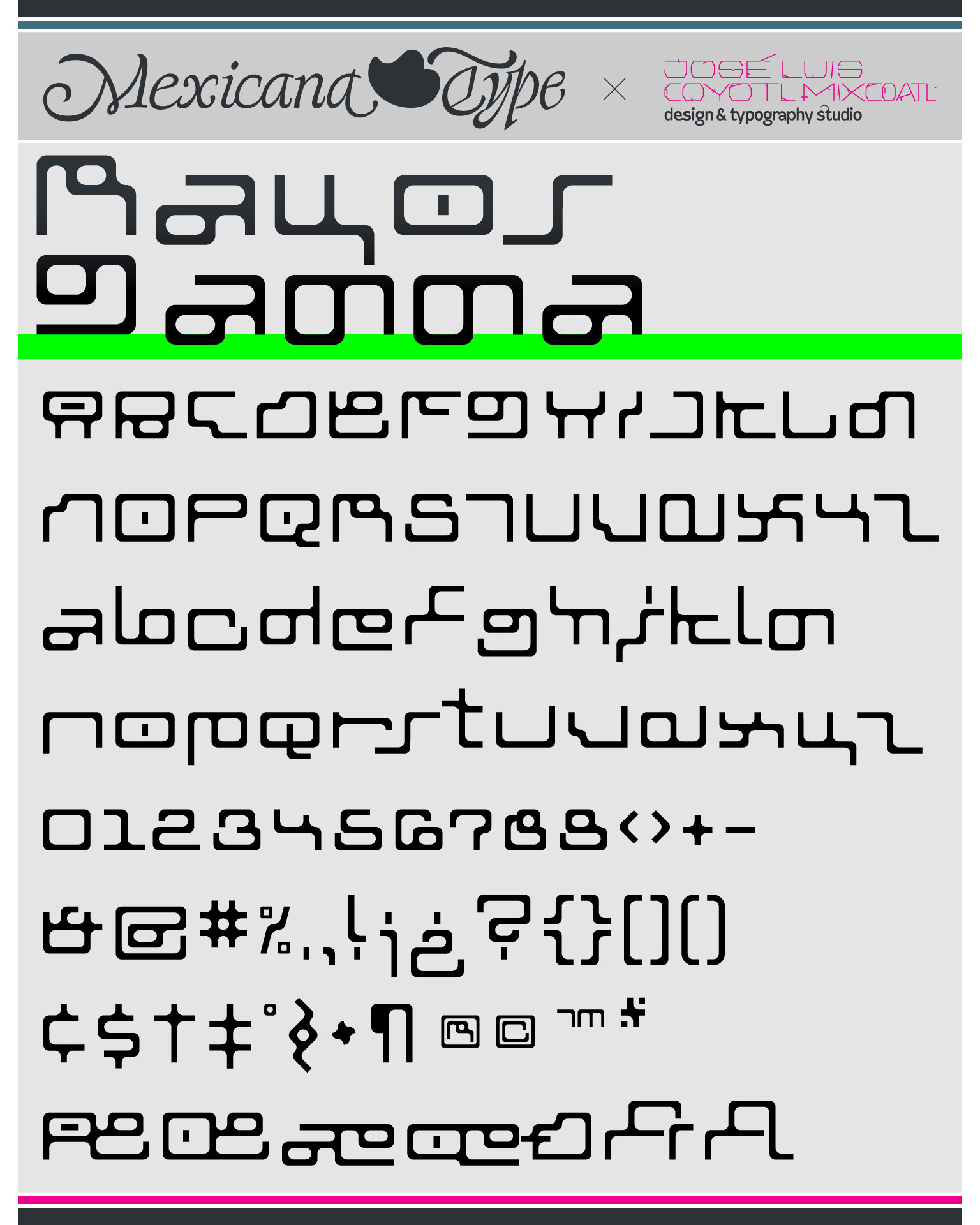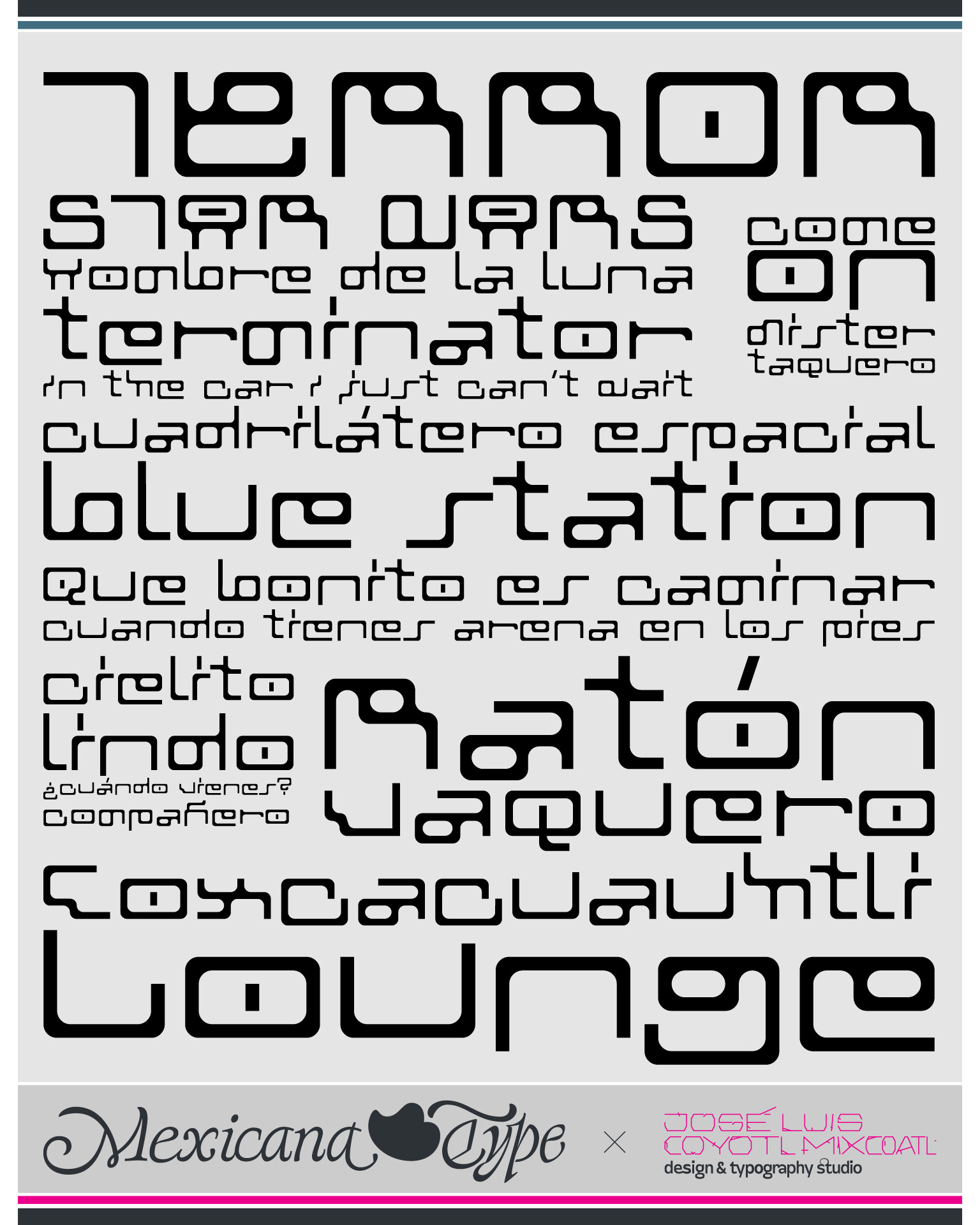
MxT Rayos Gamma es una interpretación personal del mobiliario futurista y sci-fi vintage de mediados del siglo XX, con un espíritu mas nostálgico y retro, lo que permite experimentar más con juegos de formas de las letras y lecturas intrincadas, con un ritmo mucho mas gráfico y ecléctico. Siendo un gran aficionado al diseño industrial, la estructura de las letras tiene fuertes reminiscencias a la gráfica de medio siglo, con elementos que remiten a estructuras tubulares o en madera, con cieeto aire minimalista, pero al mismo tiempo con formas que rompen la asimetría y la alineación a momentos puede parecer y estar llena de momentos provocadores.
MxT Rayos Gamma tiene la intención de que algún día, cada caracter bien pueda ser producido como objetos e incluso como muebles. La maravilla de la tipografía.